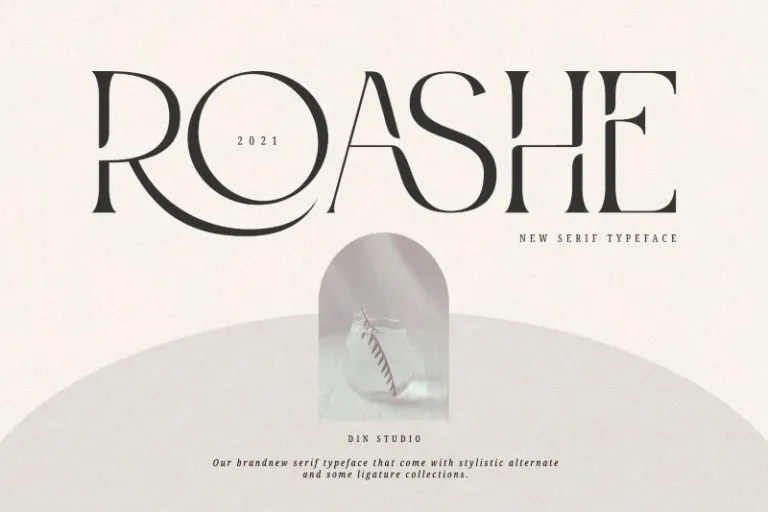
A fonte ‘Roashe’ é uma elegante seleção para quem procura uma tipografia serif que brinca com a modernidade, criando designs distintos e chamativos. Feita pelo designer Din Studio na 99designs, essa font se destaca por trazer um toque sofisticado à qualquer projeto. Roashe é perfeitamente adaptada para os títulos de páginas, posters e criações de marca, desde logotipos até designs mais amplios que precisam de uma cara moderna e arrumadinha. Seja você designer ou criador de conteúdo digital, a ‘Roashe’ é uma ótima escolha para dar um toque especial aos seus projetos, garantindo um visual atraente em qualquer aplicação. Ela vem completa apenas com caracteres maiúsculos, o que permite uma flexibilidade ainda maior na criação de layouts e materiais publicitários.